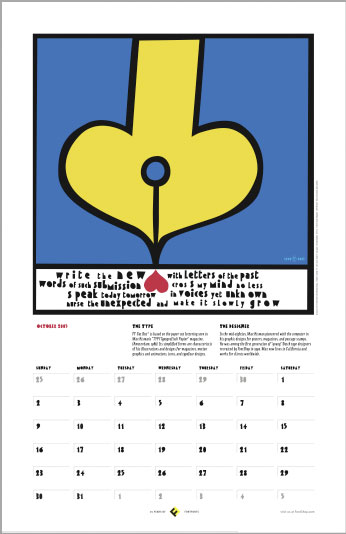
Kalenderblatt: Max Kismans goldener OktoberEben wiedergefunden: den FontFont-Wandkalender 2005.
bis Dezember nach. Der in San Francisco lebende Holländer Max Kisman
lieferte das Artwork für den Monat Oktober. Er verwendete seine Schrift